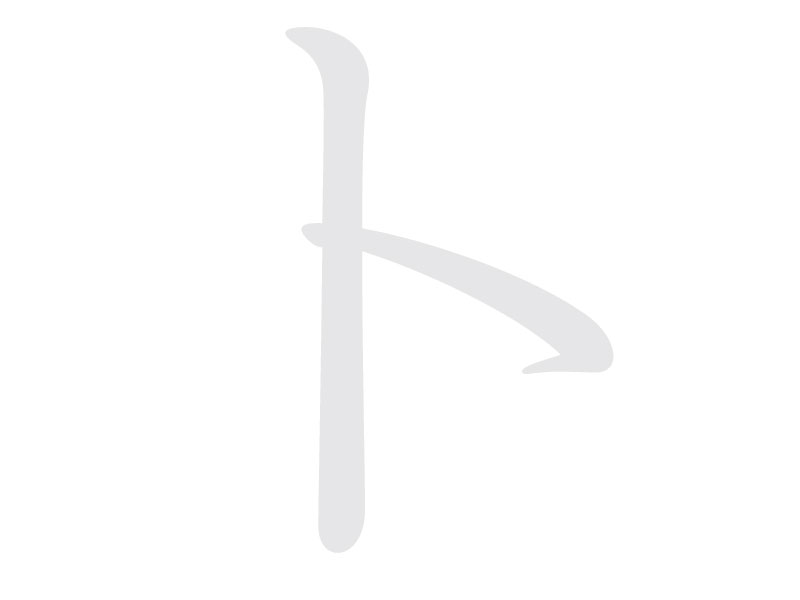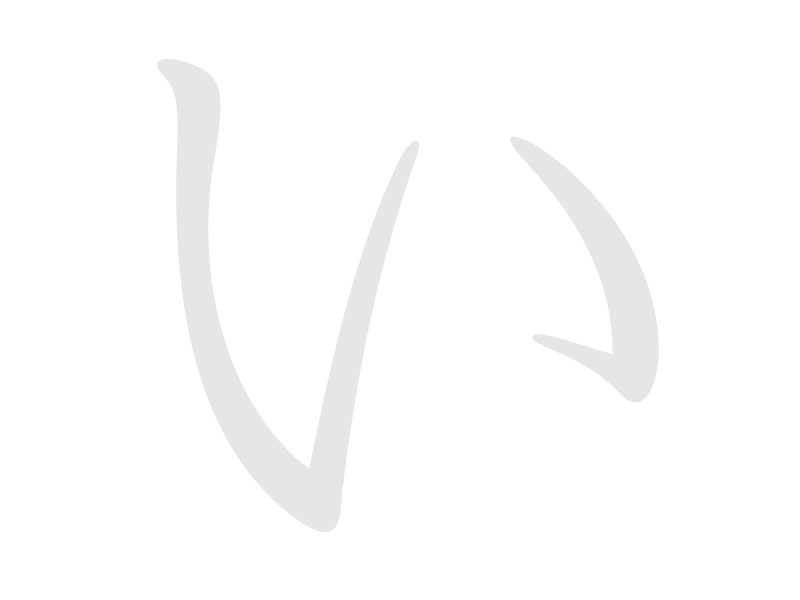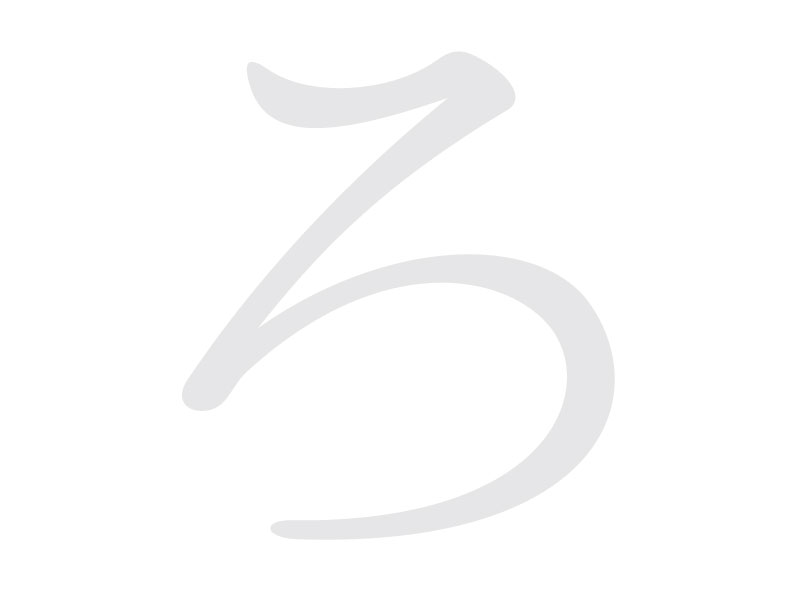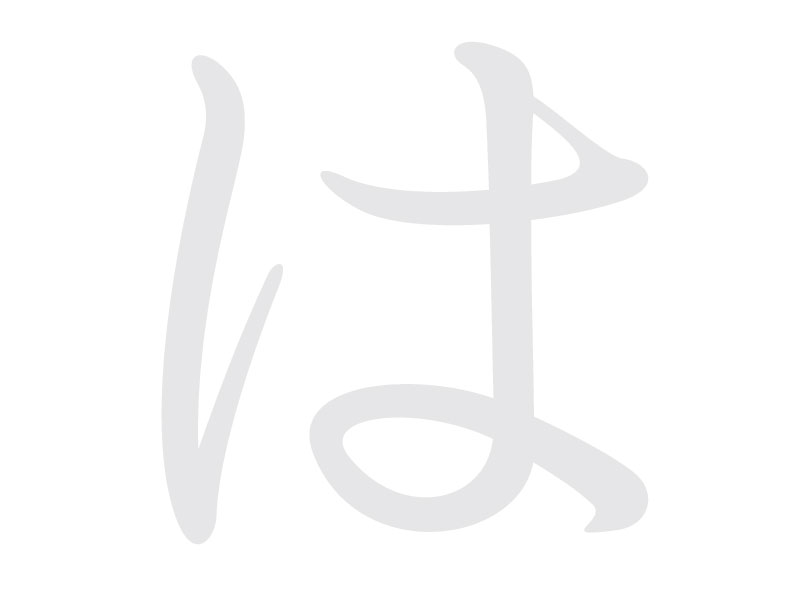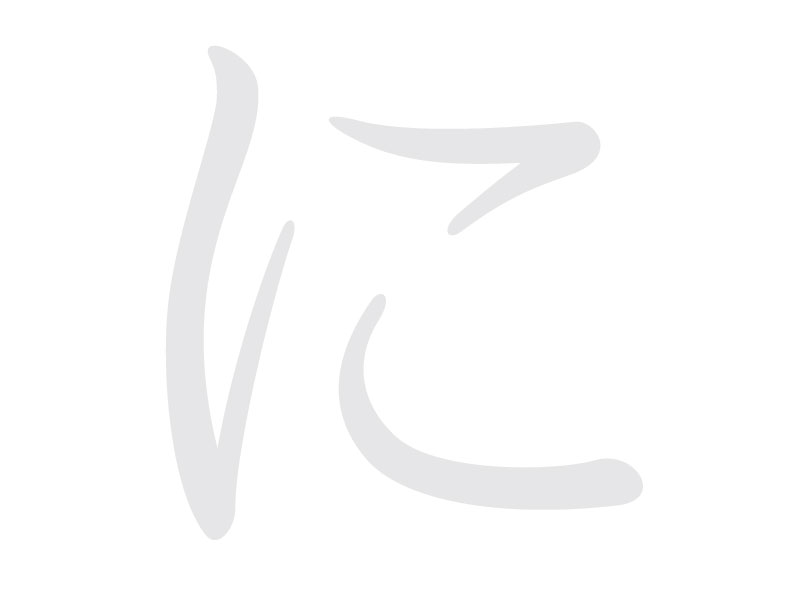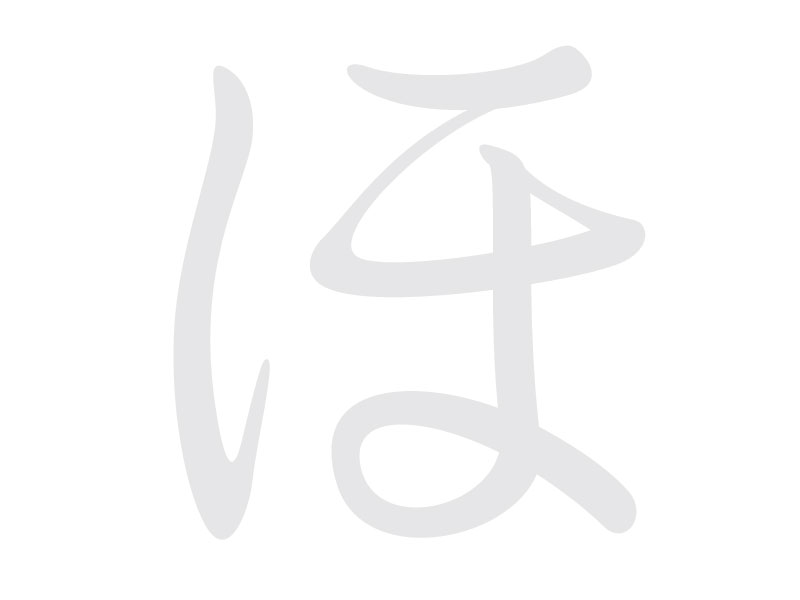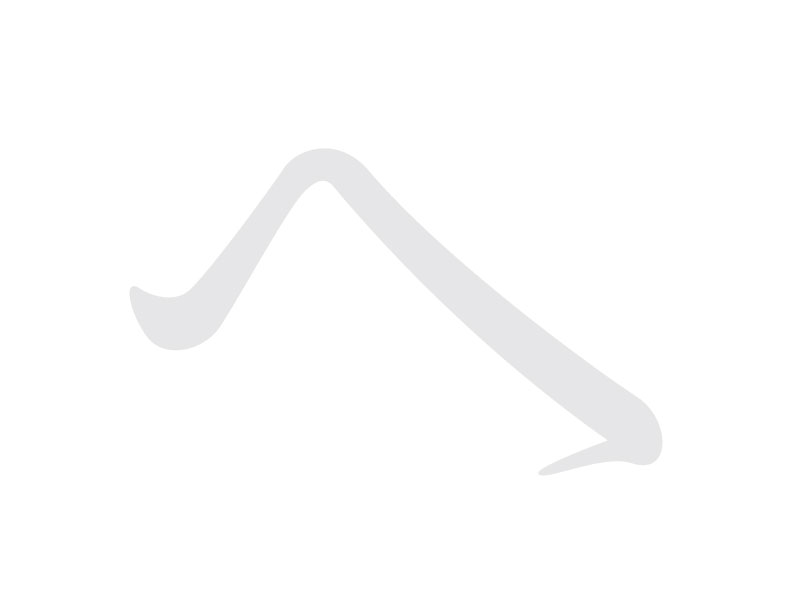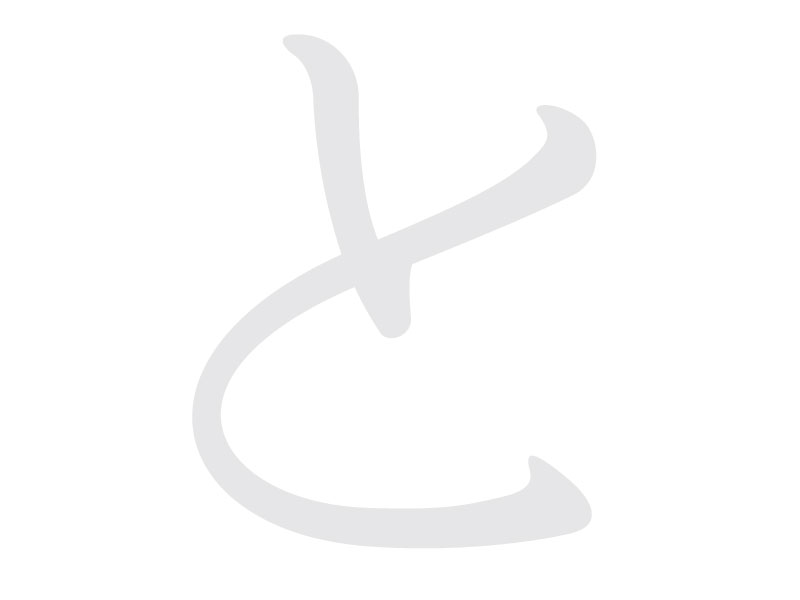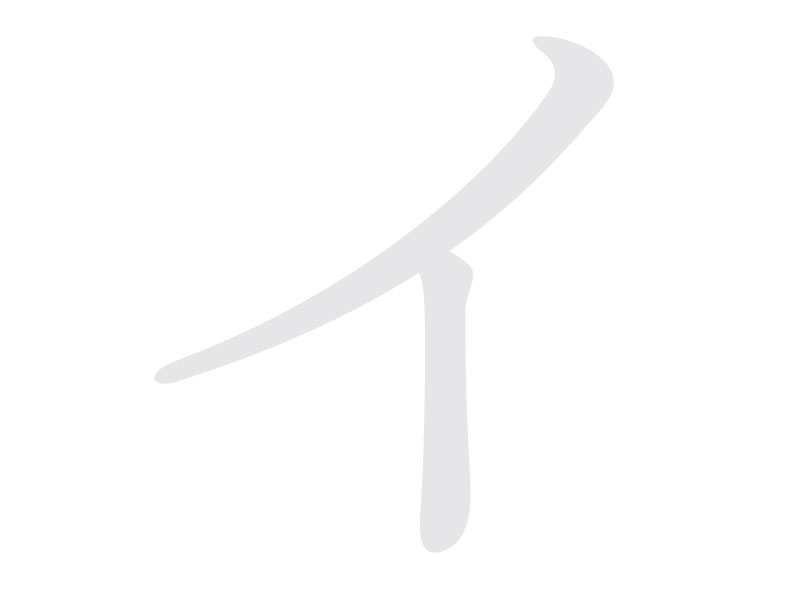
新聞明朝ふうの見出し向け仮名書体、「ぬばたまみんちょう」の公式サイトです。
「ぬばたまみんちょう」は、新聞明朝ふうの見出し向け仮名書体。
ひらがな・カタカナと、ごく一部の記号を含むオープンタイプフォントです。
かな詰めデータ(プロポーショナルメトリクス、カーニング)を搭載しています。
漢字や数字、アルファベット等は収録していません。
組み合わせ推奨書体は、筑紫新聞明朝LB(フォントワークス)、
イワタ新聞中明朝体(イワタ)、エムニュースエム(モリサワ)、TB新聞明朝M(モリサワ)です。
字面が大きいので、他の一般的な明朝体では合わないと思います。ご注意ください。
ver.2.0では、フォント作成ツールをGlyphsに変えて、
詰め情報の追加をおこない、新たに作り直しました。